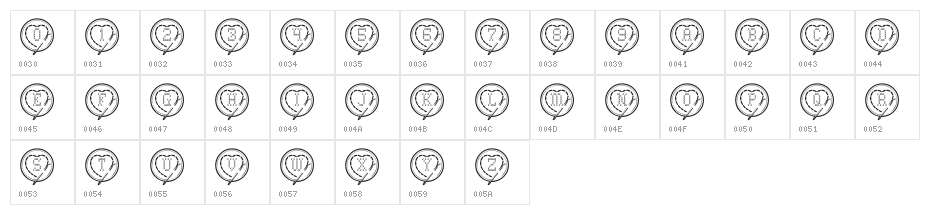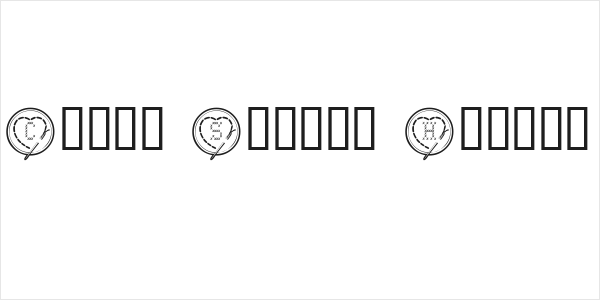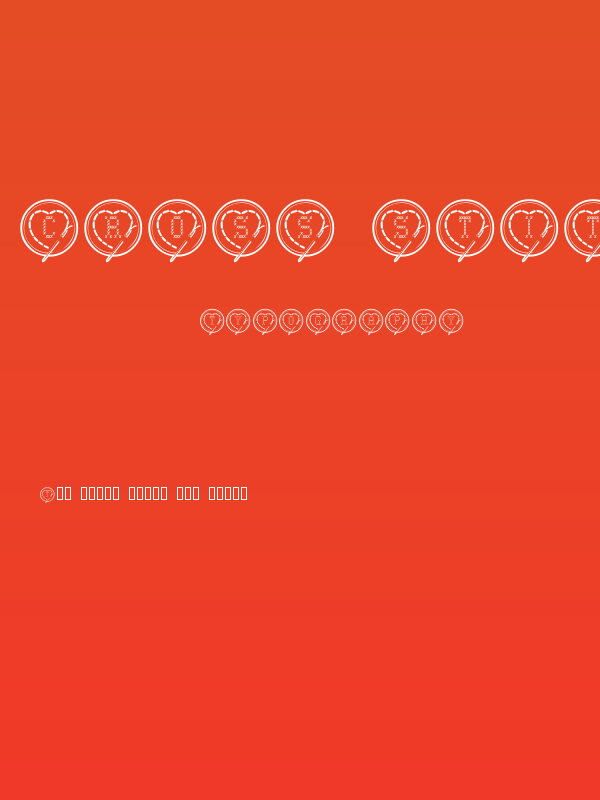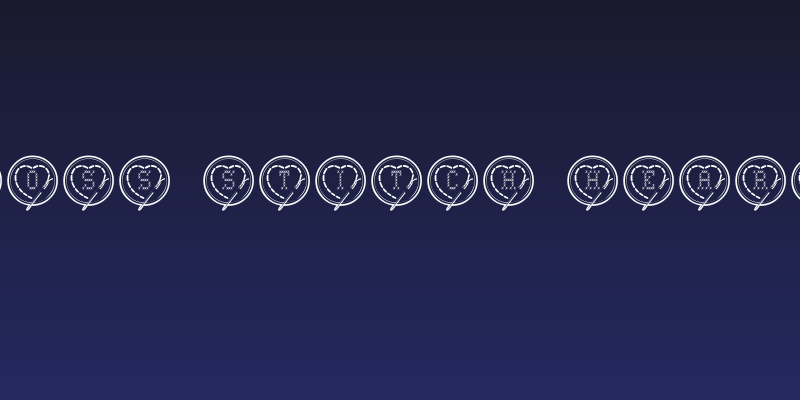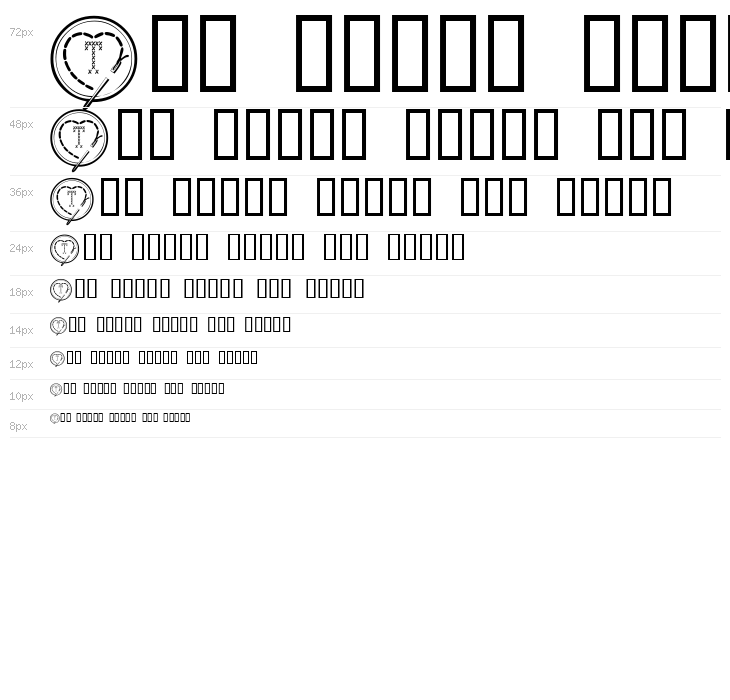
Cross Stitch Hearts Font
| समग्र शैली | Vintage |
| उपयोग का मामला | Logos, Headlines, Decorative text |
| सुझाए गए प्रोजेक्ट | Ideal for craft projects, DIY invitations, greeting cards, and any design work that seeks to evoke a handmade or vintage aesthetic. |